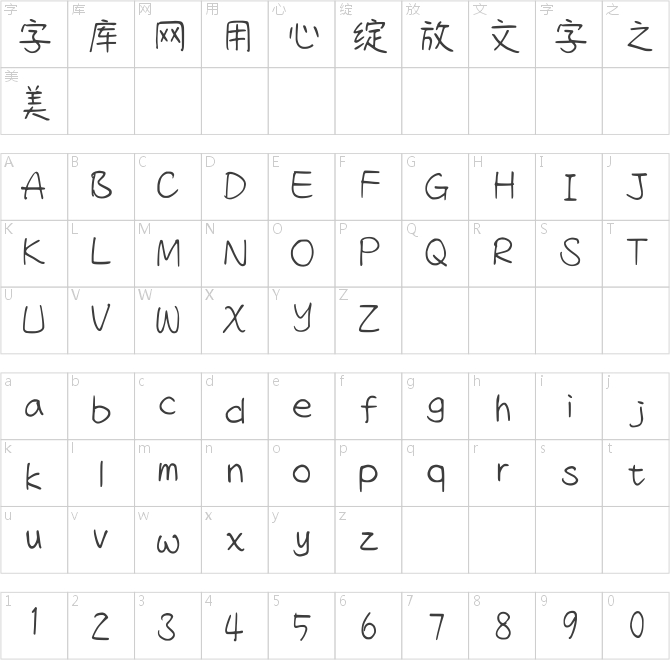
字体名称: 清松手写体2
清松手写体2
「清松手寫體」是清松在稿紙上用原子筆手寫,透過「守寫字」網站產生出初稿字型檔,再透過字型軟體後製加工而成的手寫字型。
清松手写体2字体JasonWriting2字库是一款让人赏心悦目、百看不厌的中文字体,适合各类广告和产品包装设计应用,字体大小4.83MB,格式为ttf字体,上传用户是金百诚,作者/版权方为游清松